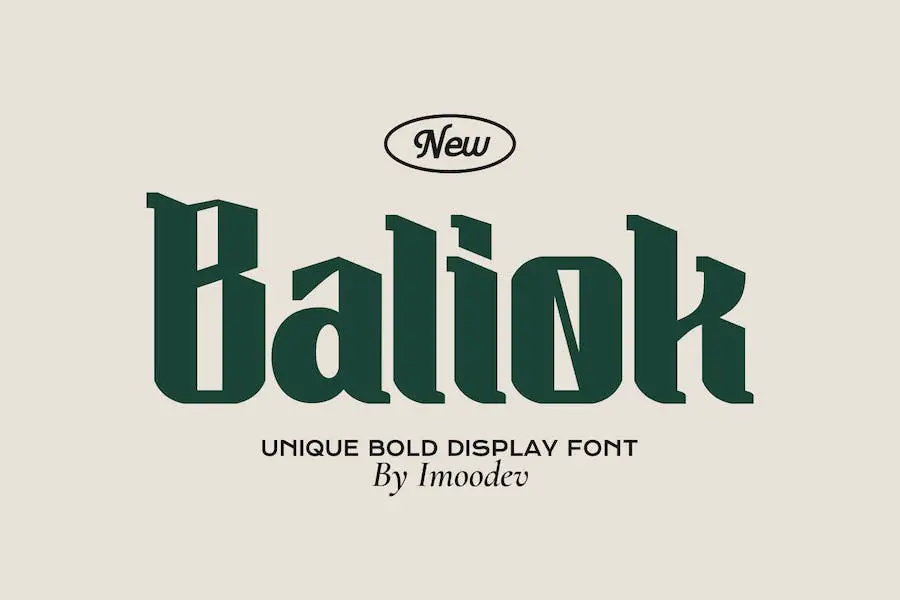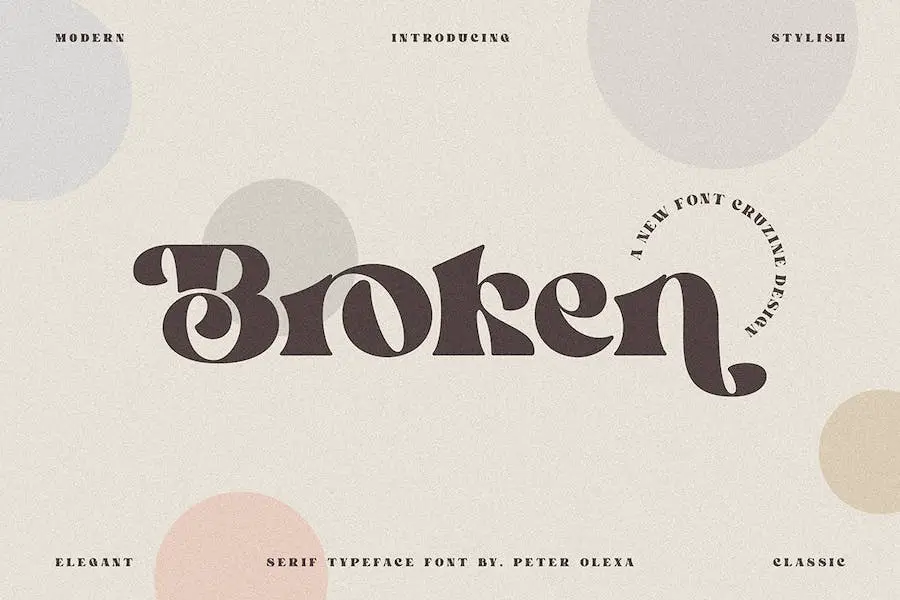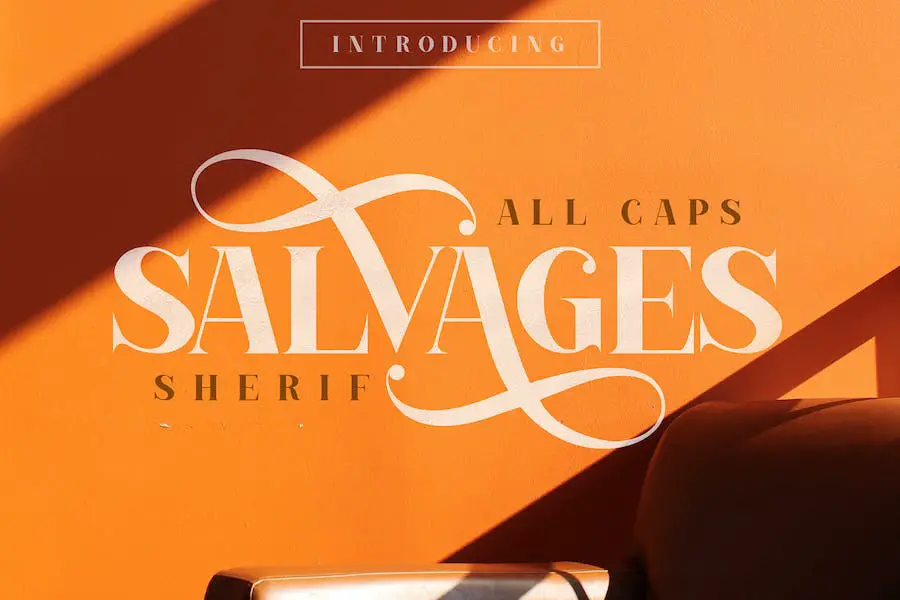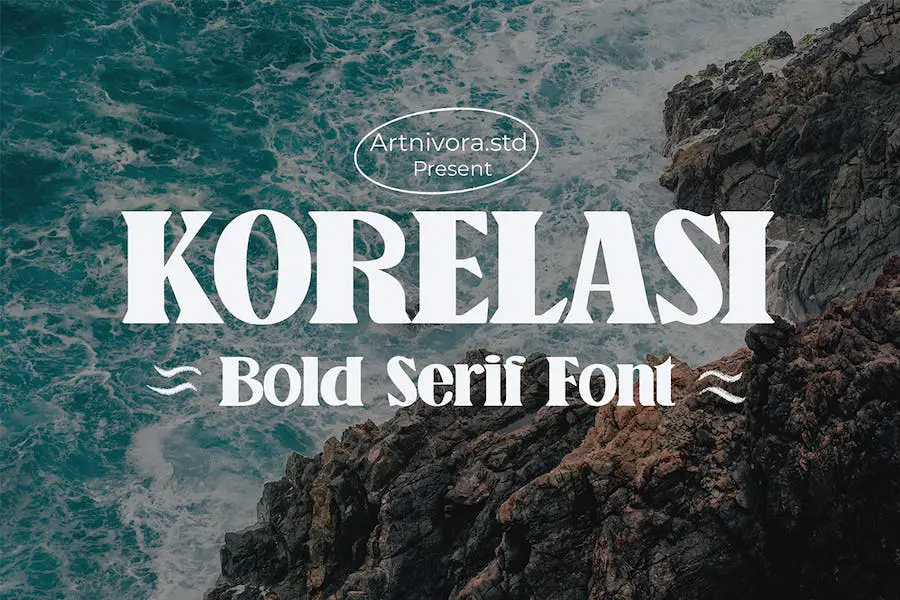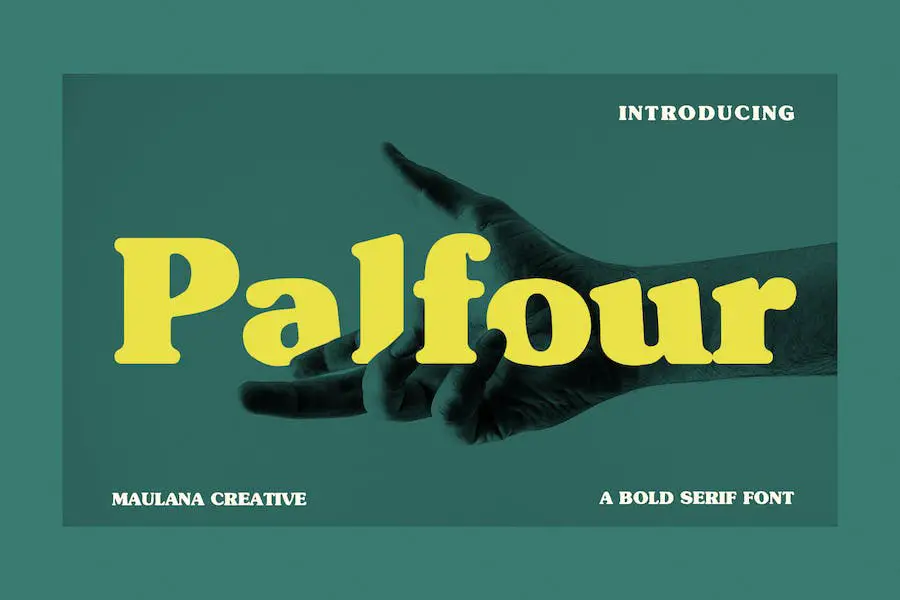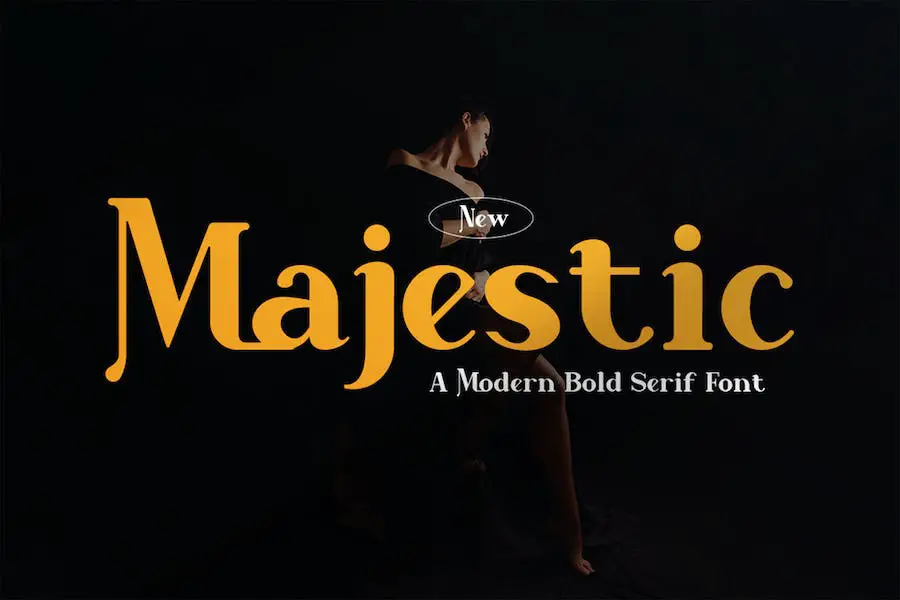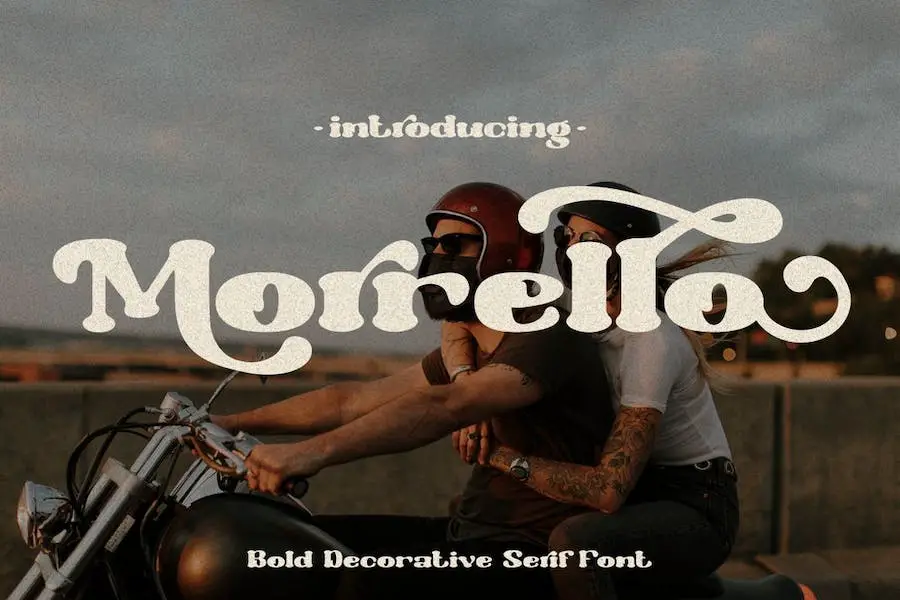
Nie szukaj dalej, ponieważ w tym poście na blogu przyjrzymy się najlepszym pogrubionym czcionkom szeryfowym, które przeniosą Twoje projekty na wyższy poziom.
Być może zastanawiasz się, co sprawia, że czcionka jest pogrubiona i dlaczego powinienem wybrać czcionkę szeryfową? Cóż, pozwól, że ci to wyjaśnię. Pogrubione czcionki świetnie nadają się do przyciągania uwagi i wyrażania opinii.
Dodają nacisku i śmiałości Twojemu tekstowi, czyniąc go wyjątkowym. Z drugiej strony czcionki szeryfowe mają małe linie lub kreski na końcach liter, co nadaje tekstowi bardziej wyrafinowany i klasyczny charakter.
W tym artykule zagłębimy się w świat odważnych czcionek szeryfowych i podzielimy się ciekawymi statystykami i faktami na temat ich popularności wśród projektantów. Zbadamy ich wszechstronność i sposób, w jaki można je wykorzystać w różnych projektach, od logo po strony internetowe.
Najlepsze pogrubione czcionki szeryfowe premium
Chcesz dodać odrobinę wyrafinowania i śmiałości do swojego kolejnego projektu? Nie szukaj dalej niż nasz starannie wybrany wybór najlepszych pogrubionych czcionek szeryfowych premium.
Krata
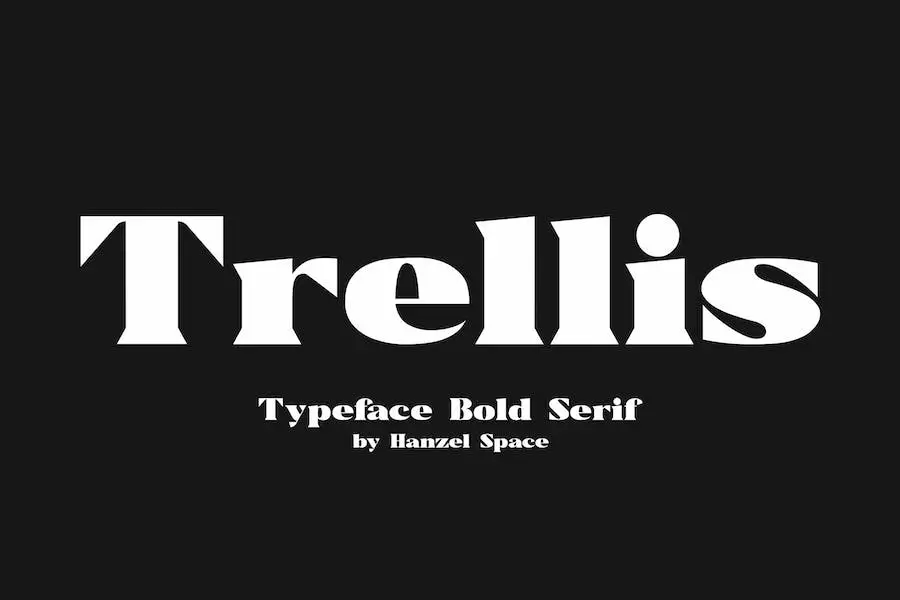
Trellis to oszałamiająca czcionka szeryfowa o nazwie It//Typeface Bold Serif, która z pewnością przyciągnie uwagę. Łączy w sobie odrobinę stylu retro z nowoczesnym charakterem, dzięki czemu idealnie nadaje się do logo, prac redakcyjnych lub projektowania stron internetowych.
Odważny i niepowtarzalny design z pewnością wyróżni Twoje projekty z tłumu. Niezależnie od tego, czy jesteś grafikiem i chcesz dodać efekt wizualny do swojej pracy, czy po prostu chcesz ulepszyć projekt swoich projektów, Trellis to doskonały wybór.
Dzięki swojej wszechstronności i przyciągającemu wzrok wyglądowi ta czcionka z pewnością przeniesie Twoje projekty na wyższy poziom.
Mieszkanie
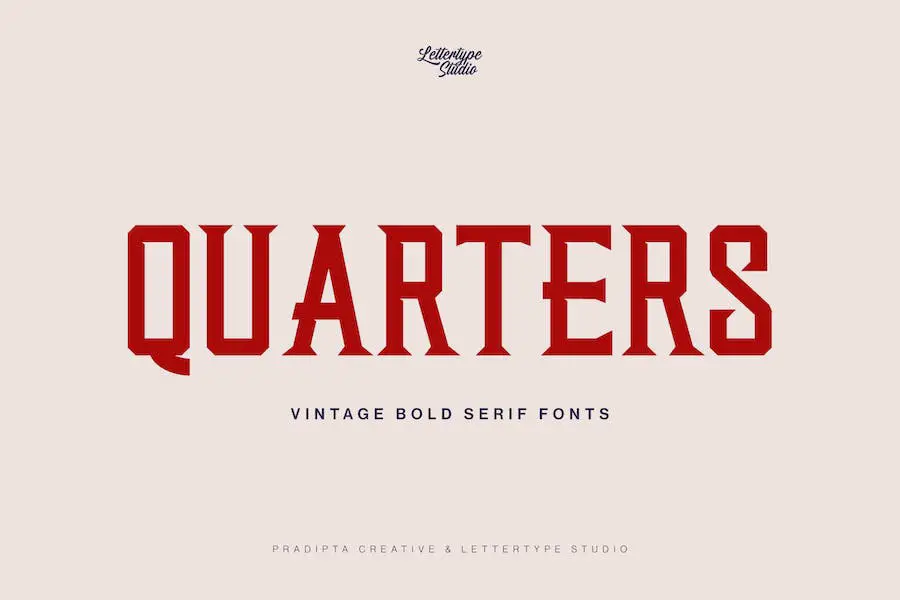
Quarters to pogrubiona czcionka szeryfowa w stylu vintage, która czerpie inspirację z kultury miejskiej i charakteryzuje się mocnymi charakterami. Dodaje elegancji i śmiałości każdemu projektowi, dzięki czemu jest idealny dla grafików, którzy chcą ulepszyć swoją pracę.
Dzięki unikalnemu stylowi i przyciągającym uwagę atrybutom Quarters wyróżnia się jako jedna z najlepszych dostępnych pogrubionych czcionek szeryfowych.
Ta czcionka oddaje esencję kultury miejskiej, nadając jej charakter vintage. Jego odważne i mocne postacie rzucają się w oczy i przyciągają uwagę. Niezależnie od tego, czy pracujesz nad logo, stroną internetową, czy jakimkolwiek innym projektem, Quarters wyniesie Twoją pracę na nowy poziom.
Quarters łączy w sobie to, co najlepsze z obu światów – klasyczny styl czcionki szeryfowej i śmiałość współczesnego designu. Czyste linie i ostre krawędzie nadają mu nowoczesny charakter, zachowując jednocześnie jego zabytkowy urok. Zapewnia właściwą równowagę pomiędzy elegancją i miejskim charakterem.
Kigery
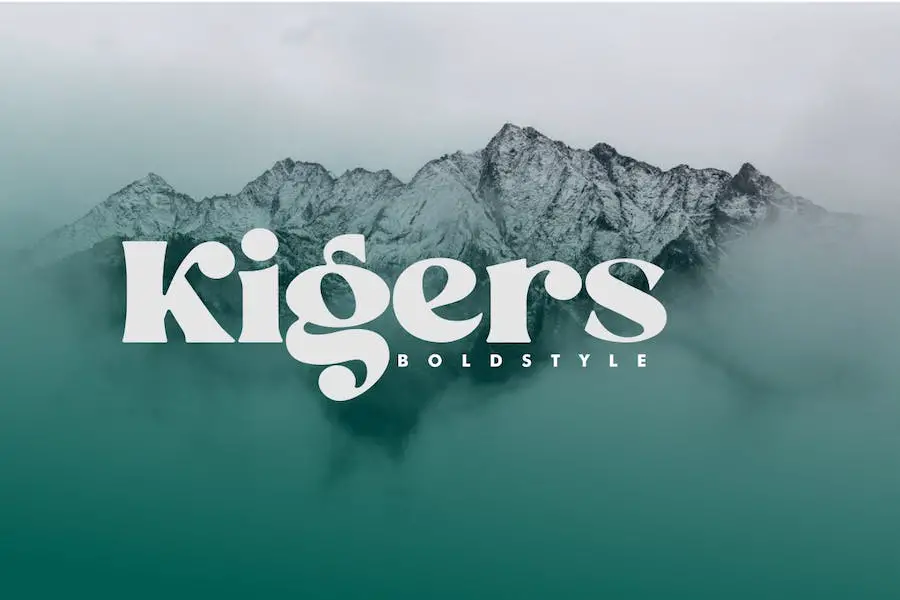
Kigers to oszałamiająca i potężna czcionka szeryfowa, idealna do ulepszania projektów. Ta czcionka jest idealna dla grafików, którzy chcą dodać swoim pracom odrobinę wyrafinowania i elegancji.
Dzięki prostemu, ale odważnemu wyglądowi Kigers można wykorzystać do wielu celów, w tym do projektów logo, układów magazynów, postów w mediach społecznościowych, broszur i nie tylko.
Tym, co odróżnia Kigers od innych czcionek szeryfowych, jest unikalne połączenie prostoty i piękna. Emanuje ponadczasową elegancją, która natychmiast przyciąga wzrok. Odważny charakter tej czcionki sprawia, że idealnie nadaje się do nagłówków i typografii, które muszą przyciągać uwagę i wywierać silny wpływ.
Niezależnie od tego, czy projektujesz profesjonalne logo, czy tworzysz przyciągającą wzrok grafikę do mediów społecznościowych, Kigers jest idealną czcionką, która zapewni styl i przejrzystość przekazu Twojej wiadomości.
Jego przejrzysta i prosta konstrukcja pozwala wyróżnić Twój tekst, zachowując jednocześnie poczucie elegancji i profesjonalizmu.
Dzięki Kigers możesz przenieść swoje projekty projektowe na wyższy poziom. Ta czcionka podniesie poziom Twojej pracy i nada jej wyjątkowego charakteru. Więc na co czekasz? Dzięki Kigerom nadaj swoim projektom odważny i wyrafinowany wygląd, na jaki zasługują.
Flunoza
Fluminose to fantastyczna czcionka, która ulepszy wygląd Twoich projektów. Dzięki zestawowi wielkich i małych liter szeryfowych oferuje szeroką gamę glifów interpunkcyjnych, cyfr i obsługę wielu języków.